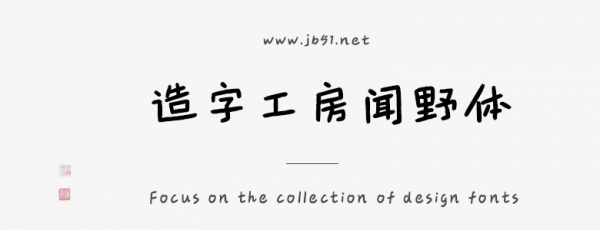
造字工房聞野體由上首造字字庫(kù)出品的字體,字體筆畫柔和,結(jié)構(gòu)舒展靈活,風(fēng)格自然雋永,運(yùn)筆流暢活潑,排版時(shí)節(jié)奏輕快,適合應(yīng)用于平面宣傳設(shè)計(jì)、網(wǎng)頁(yè)設(shè)計(jì),書法字帖等領(lǐng)域,需要的朋友可以前來(lái)本站下載。
造字工房聞野體,筆畫柔和,結(jié)構(gòu)舒展靈活,風(fēng)格自然雋永,運(yùn)筆流暢活潑,排版時(shí)節(jié)奏輕快,增加了字體灑脫、松弛的氛圍感,是一款辨識(shí)度高、風(fēng)格出眾的字體。本字體為簡(jiǎn)體字庫(kù),采用OpenType/CID格式,Adobe-GB1-5編碼?;谥腥A人民共和國(guó)GB2312-80字符集標(biāo)準(zhǔn),另按需添加101個(gè)漢字。共收容字?jǐn)?shù)6864CJK漢字,ASCII常用字符100個(gè)。